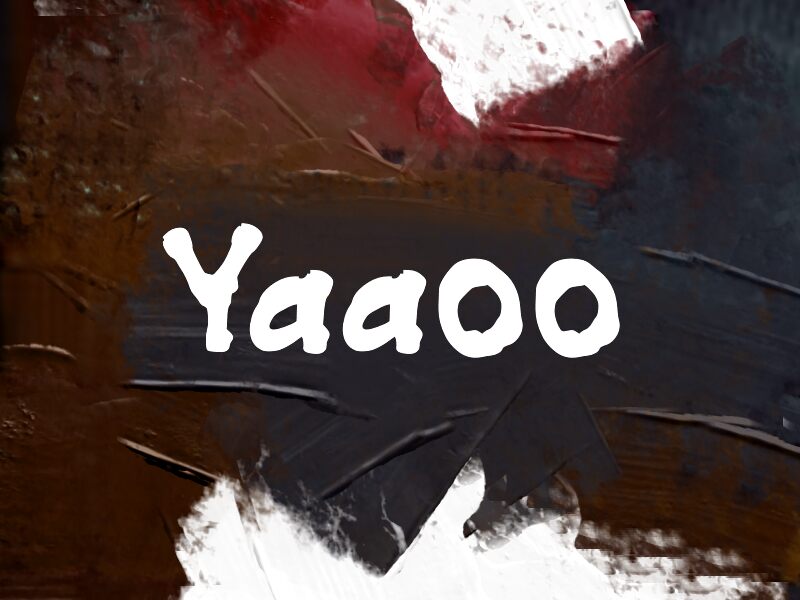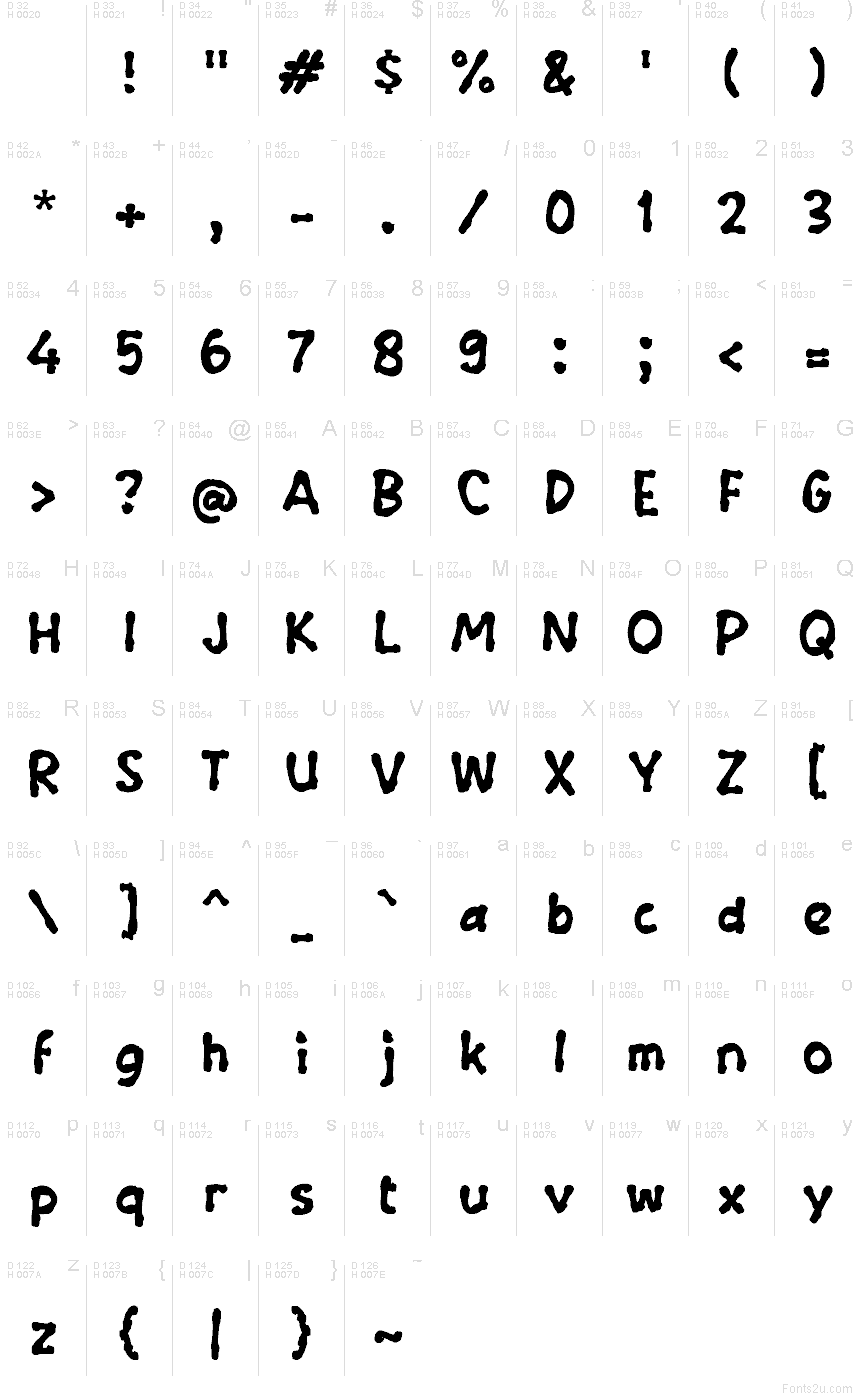
Yaaoo
Yaaoo by Wep é uma fonte brush gratuita com um ritmo denso e carregado de tinta, conferindo às letras um aspecto pressionado e ligeiramente irregular, em vez de um acabamento perfeitamente desenhado. As massas arredondadas e as bordas desiguais mantêm uma textura suave e orgânica em todo o conjunto, proporcionando um visual de marcador feito à mão, longe da rigidez da caligrafia tradicional.
Essa textura larga e acolhedora funciona muito bem em cartazes infantis, embalagens de snacks, menus de cafés casuais, miniaturas de YouTube e gráficos estilo autocolante, onde uma precisão excessiva pareceria fora de lugar. Títulos curtos e logotipos divertidos beneficiam-se especialmente das formas de pincel volumosas, que preenchem o espaço rapidamente e conferem às palavras um toque amigável e artesanal.